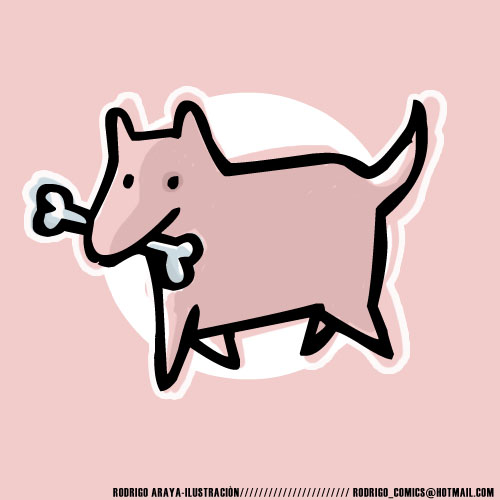
Font name: | Kiltro |
Categories | Dingbats, Animals |
Author: | Rasdesign |
Note by Rasdesign | |
esta tipografia esta basada en algo que siempre vemos , los perros callejeros aqui en chile llamados " kiltros" estos perros aparte de ser divertidos son cariƱosos . |